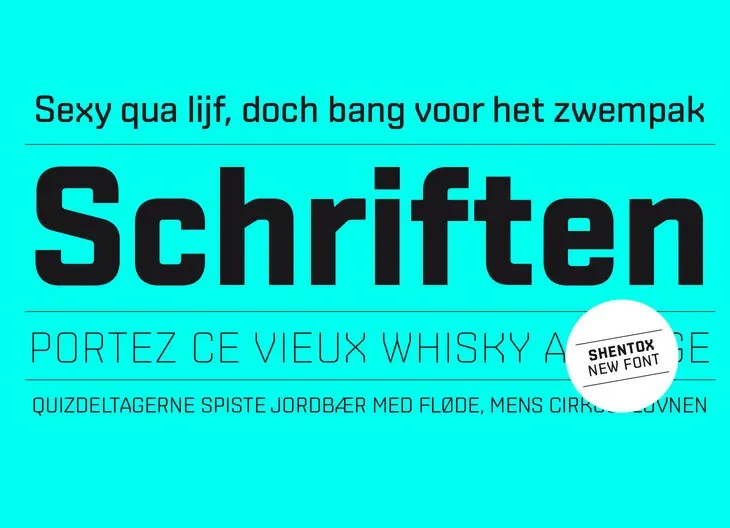
Introduzimos a Fonte Sans Serif Família. Esta fonte está inspirada na geometria com elementos humanistas quentes que garantem uma escolha perfeita para quando precisamos de um tipo serif moderno e contemporâneo. Em 2008, durante minha visita à Londres, fui apaixonado pela fonte quadrada usada nas placas de número do automóvel inglês. Fiquei inspirado a começar a trabalhar nesta fonte, que desde então vem evoluindo em intervalos regulares. Hoje, ela finalmente se tornou o Shentox. Várias outras visitas à Londres fizeram parte dessa jornada de desenvolvimento e, agora, Shentox oferece um novo recurso gráfico para você explorar.